Что такое статические или новостильные антиквы?
Шрифты с засечками, созданные под влиянием процессов рисования и гравировки. Это антиквы периодов позднего неоклассицизма и реализма (конец XVIII века). Хотя формообразование не связано с процессом письма напрямую, тип контраста в таких шрифтах соответствует логике письма острым пером. Новостильные антиквы можно узнать по вертикальным осям овалов, закрытой апертуре, каплям в окончаниях штрихов, высокому контрасту и тонким
IBM Plex Serif
Майк Эббинк, Bold Monday, Александра Самуленкова
Пара к неогротеску IBM Plex — в Plex Serif используется схожий подход к графике и формообразованию. Дизайн обоих шрифтов во многом обращается к истории IBM, цитирует её графические артефакты и в целом пытается отразить роль компании как проводника между человеком и машиной.
Практика В графике IBM Plex
Капли в окончаниях штрихов, прямоугольные засечки, вертикальные оси овалов позаимствованы из графики классической новостильной антиквы
На курсив — настоящий, независимый от прямого
Учитывая количество влияний на графику IBM Plex Serif, авторы классифицируют шрифт как «гибридную антикву».
В составе IBM Plex Serif только стандартные табличные цифры с альтернативами, верхние и нижние индексы, много готовых дробей, знаков валют, необходимые математические символы.
Начертания 7 степеней насыщенности от Thin до Bold с курсивами.
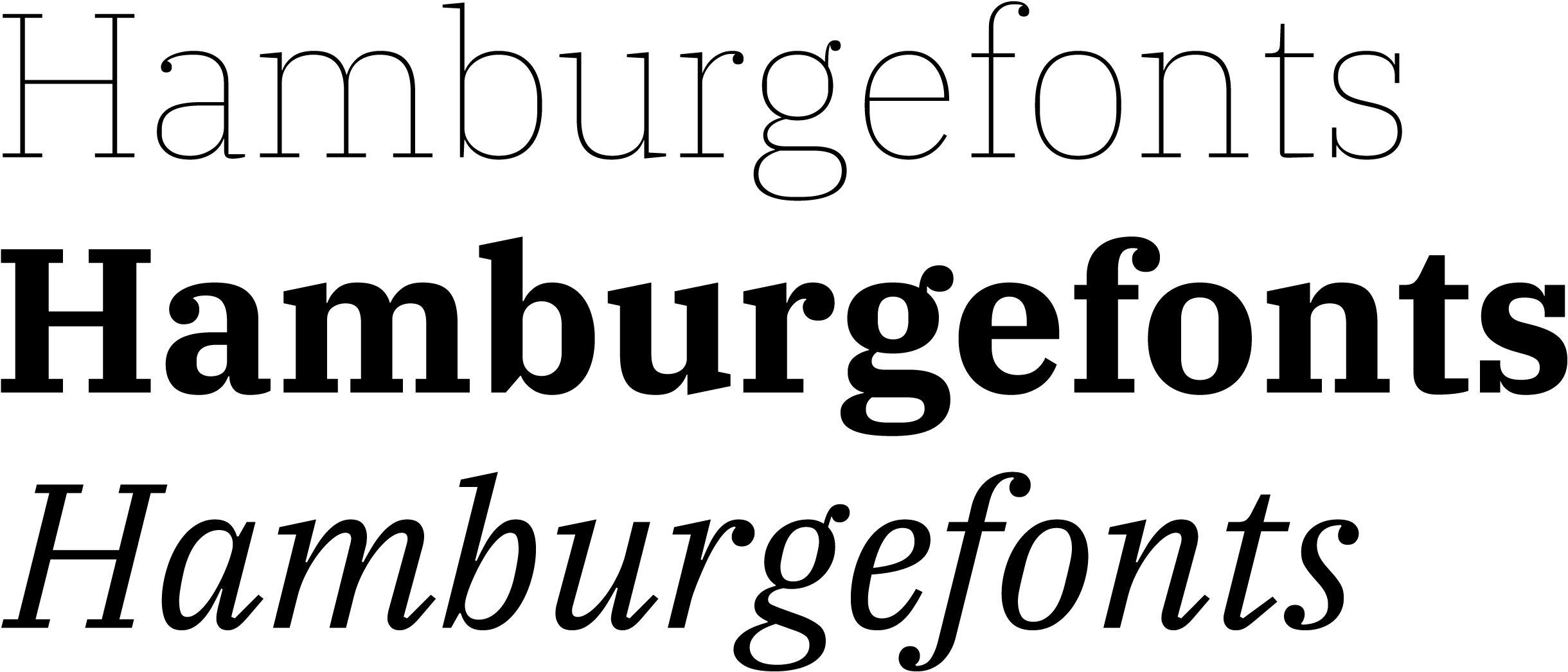
Кириллица в шрифте качественная и сбалансированная, с грамотным выбором конструкций и решений.
Несколько странным кажется разный рисунок строчной и прописной Чч.
С ростом насыщенности возникают проблемы в диакритике для украинского языка.
Перекладина в частях буквы Њњ сербского и македонского
Наш совет
IBM Plex Sans — качественный шрифт для широкого спектра применений, но языковая поддержка в кириллице страдает из-за точечных недочётов.
Prata
Иван Петров, Cyreal
Акцидентная новостильная антиква с нетипичным подходом
Практика Качество кривых, пропорции и работа с межбуквенными
Жёсткое присоединение арок к вертикальным штрихам несколько контрастирует с гладкими присоединениями в овальных знаках.
В единственном прямом начертании: расширенные латиница и кириллица, обычные пропорциональные цифры, только необходимый минимум дробей и знаков валют.
Кириллица Качественная, естественная, с уместными в акцидентном наборе конструкциями.
Несмотря на широкий знаковый состав, шрифт не подойдёт для набора на таджикском и абхазском языках из-за отсутствия знаков Ҳҳ.
Непривычно выглядит окончание с засечкой в украинской є, есть и типичные проблемы с диакритикой.
Prata не балует пользователя широкими возможностями или количеством
Old Standard TT
Алексей Крюков
Шрифт воссоздаёт общий характер классицистических гарнитур XIX
Несмотря на субъективность этого подхода, ассоциации с прошлым действительно в шрифте есть: он заимствует графику и заигрывает с названием распространённой советской гарнитуры «Обыкновенная новая».
Практика Высокий контраст и низкие зауженные строчные
В Old Standard невысокое качество кривых, мятые контуры.
Непоследовательна работа с формой и деталями в начертаниях разной насыщенности.
Знаковый состав: расширенные латиница
Начертания В Old Standard три начертания: Regular, Italic и Bold.
В жирном начертании очевидны избыточные межбуквенные расстояния.
Кириллица Конструкции знаков в кириллице ожидаемые и соответствуют тому, что мы привыкли видеть в исторических образцах новостильных антикв, однако исполнение нельзя назвать идеальным.
Капля в верхней ветви к скомкана, хвост в б задранный и слишком лёгкий.
Слишком длинный верхний горизонтальный штрих в ъ. Лишние скругления над правыми свисающими элементами в Дд Цц и родственных знаках. Похожее скругление в верхнем левом углу Дд и Лл дополнительно ломает диагональный
Очень длинный горизонтальный штрих в ъ, слева от которого образуется дыра. Дисбаланс внутреннего белого в м — диагонали прижались к вертикальным штрихам.
Несколько проблем прямого начертания перетекли
Нижняя часть Ђ скомкана — элементам в ней тесно.
Типичные проблемы с диакритикой в наборе на украинском языке.
Brygada 1918 — интересный проект с точки зрения исследования и возрождения шрифтового наследия, однако кириллица в нём проигрывает латинице в качестве. Использовать её не стоит.